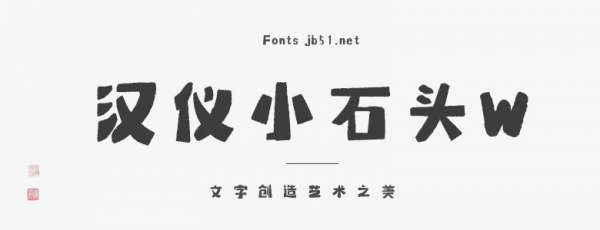
漢儀小石頭W是一款賞心悅目、百看不厭的書(shū)法藝術(shù)字體,字體線條粗細(xì)適中,筆畫(huà)隨性,結(jié)構(gòu)肆意灑脫,具有很好的視覺(jué)感,適合于文化類(lèi)的宣傳設(shè)計(jì)、商業(yè)類(lèi)品牌的廣告和產(chǎn)品包裝設(shè)計(jì)以及個(gè)性化文字排版等較多場(chǎng)景。